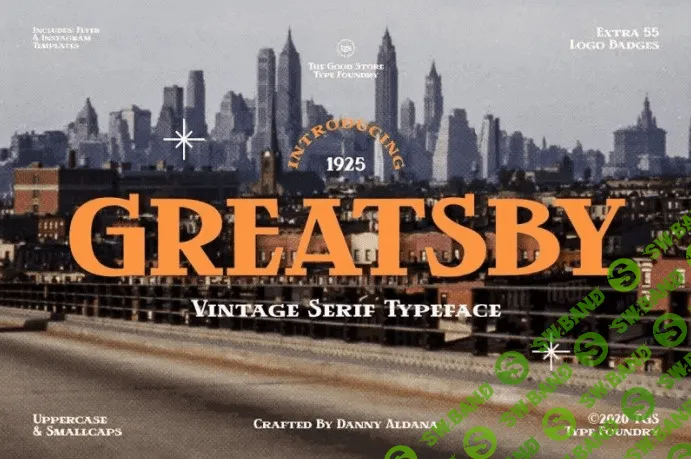
Название: Greatsby Font
[Creativemarket] Greatsby Font
Greatsby Typeface - это Vintage Serif Display Typeface, вдохновленный многими старинными обложками романов 1920-х годов.